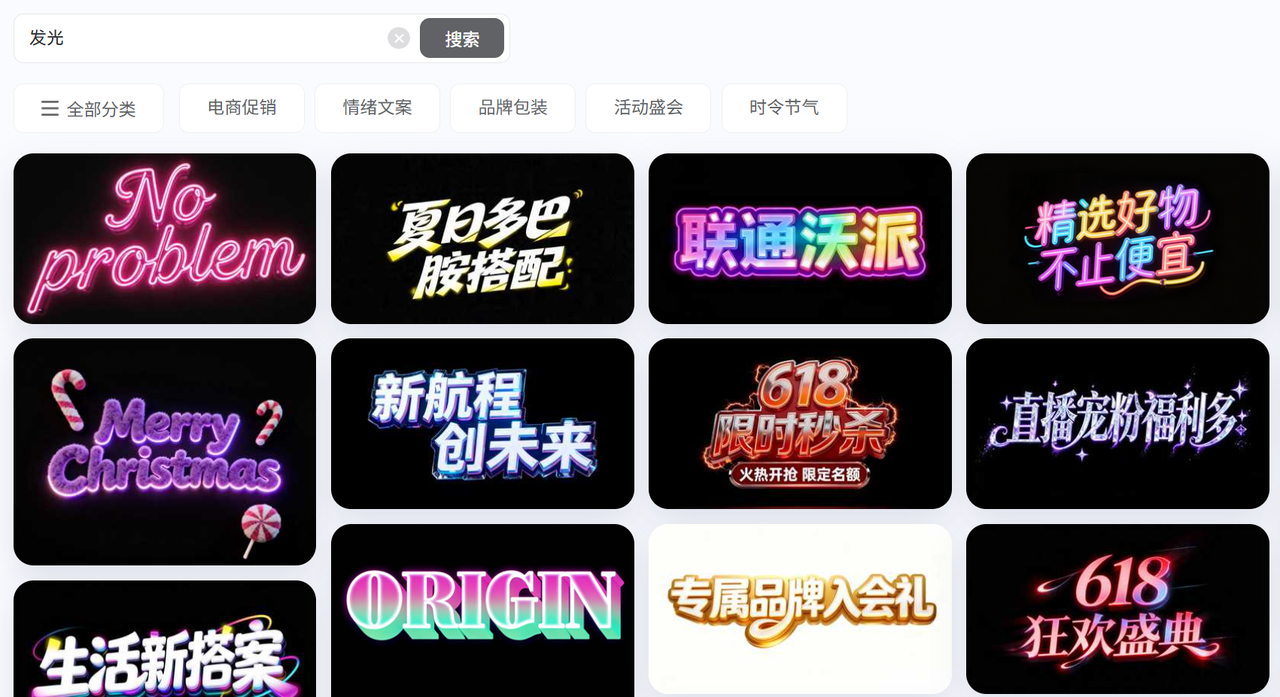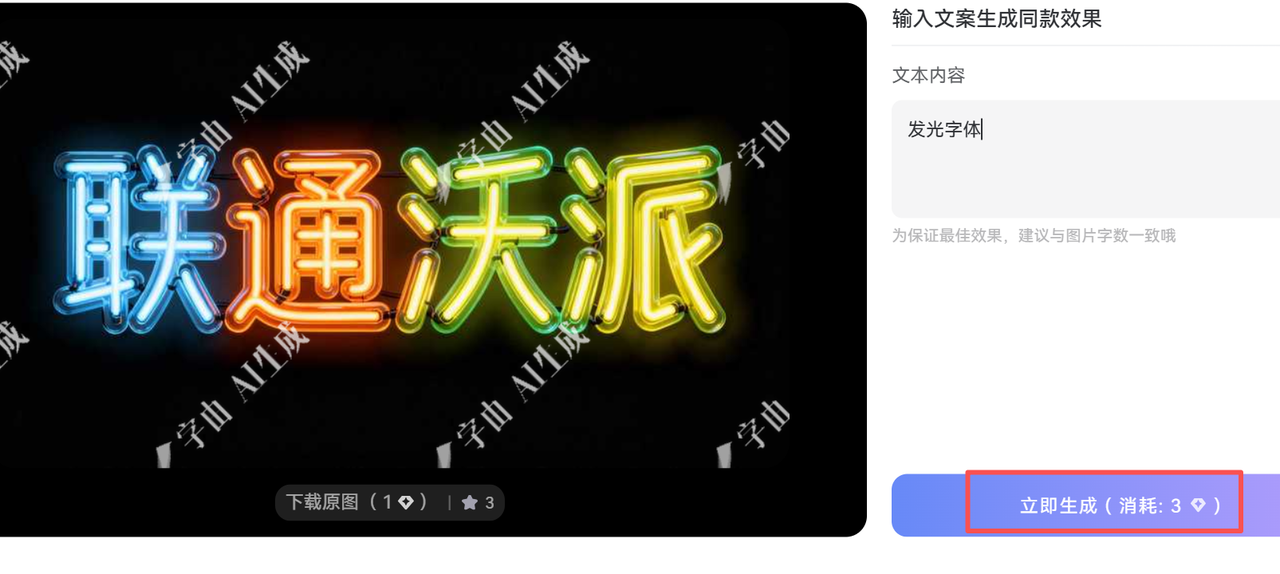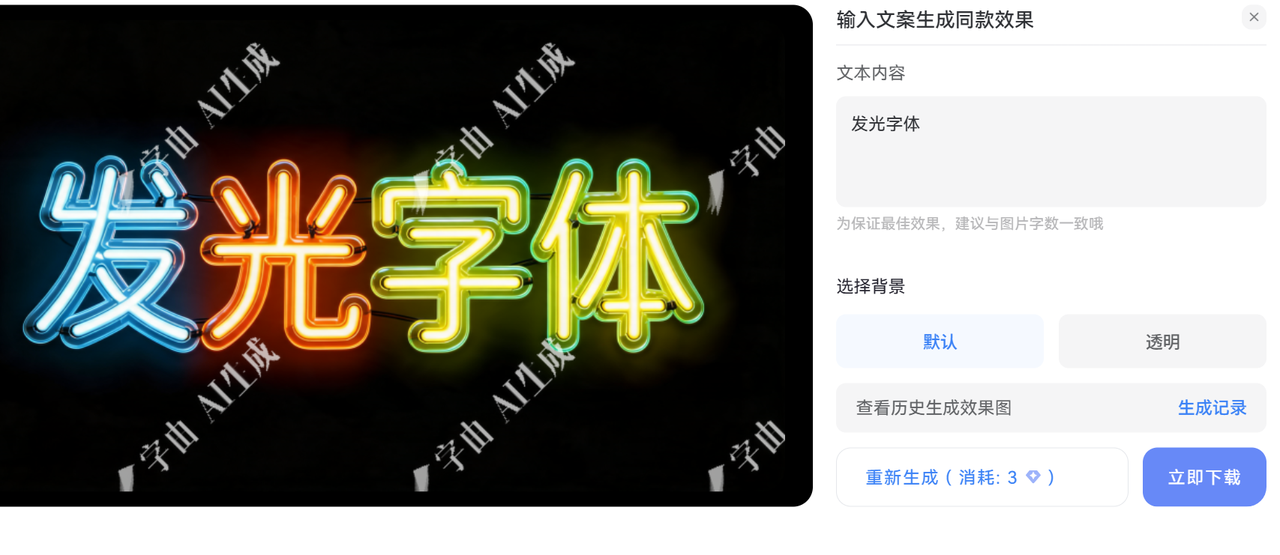
免费商用发光字体下载教程,AI生成发光字体方法
发光字体,因为其独特的光影效果,能够瞬间提升视觉冲击力和美感。然而,许多设计师和创作者在寻找免费且可商用的发光字体时,非常困难,作为一名长期从事设计和内容创作的人,今天,我将分享一个完整的免费商用发光字体下载教程,帮助你快速获取合适的字体资源,掌握简单的发光效果制作方法,掌握这些内容后,你可以轻松应用发光字体于海报、网页、视频甚至品牌标识设计,提升作品的专业度和吸引力。
一、字由AI字体
字由AI字体是一种基于人工智能技术的字体生成与设计平台。平台提供多种字体模板,涵盖现代、复古、手写等多样风格。无需手动绘制,快速生成所需字体,大幅节省设计时间。对于想要制作发光字体效果的朋友来说,字由AI生成字体是个非常好的选择
二、发光字体下载
访问官网
搜索发光字体
页面内置多款字体模板,搜索栏可输入“发光字体”或“光影字体”关键词筛选。
选择合适字体
挑选你喜欢且符合设计主题的发光字体
生成发光字体
输入自己的文字,点击一键生成,等待几十秒后就可以完成字体生成
下载发光字体
点击下载按钮,即可把字体下载到本地,方便应用到你的作品中
通过以上步骤,你可以获得质量较高、且无版权顾虑的发光字体文件。在设计中直接使用这些字体,既节省时间又保证合规。
三、常见发光字体模板推荐
最近我使用字由AI字体比较多,给大家分享几款我认为比较好看的发光字体模板。
心动好礼,为爱放价
比较典型的有关“爱”的节日宣传都可以使用,比如520、情人节、母亲节、父亲节等等
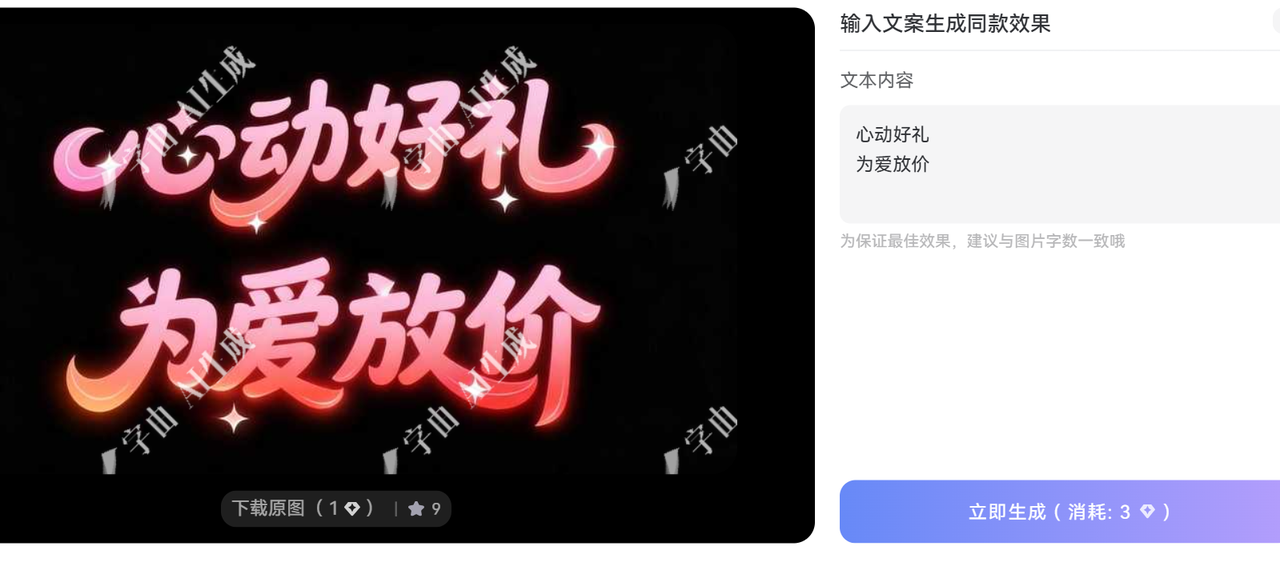
电音派对
适合电音、说唱、嘻哈等潮流场景
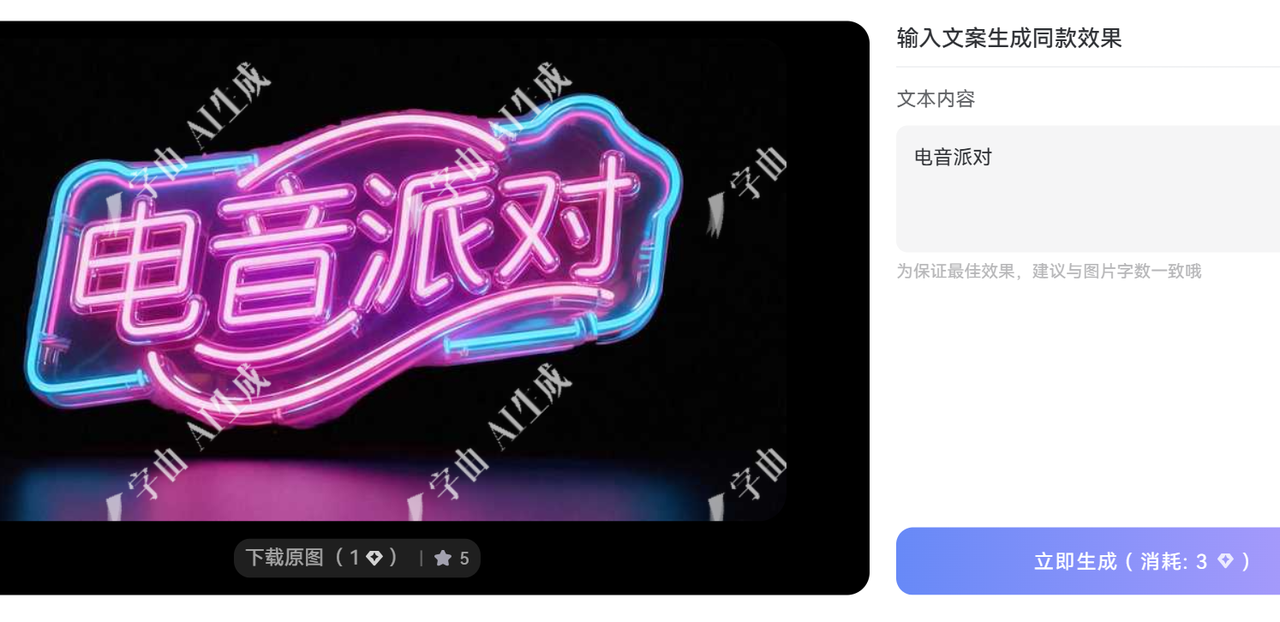
星光游乐园
适合综艺、娱乐等方向
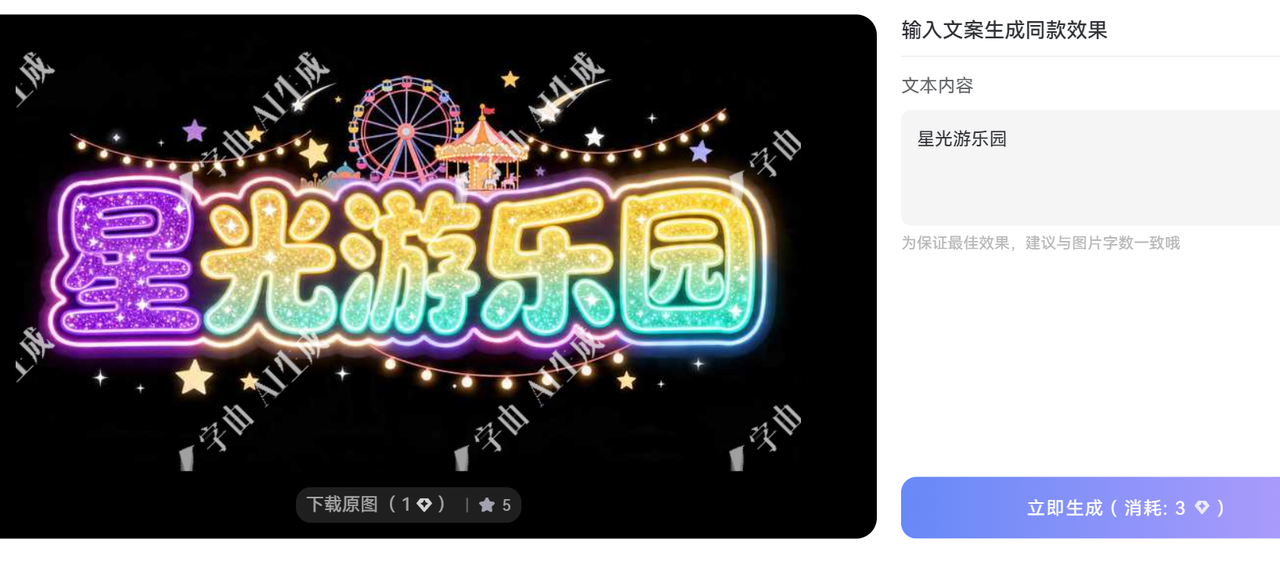
四、AI生成发光字体的常见问题
在使用过程中,我也遇到并总结了一些常见问题,希望能帮到你:
Q2:AI生成的发光字体能修改颜色和大小吗?
A:一般导出的图像文件颜色固定,若想更改需在矢量编辑软件中调整。
Q3:AI生成的发光效果会不会显得不自然?
A:不会,只要你选择匹配的发光字体模板,你就可以生成同款的效果,不会显得不自然
通过本文,我分享了免费商用发光字体下载的实用方法,并介绍了利用AI技术生成发光字体的技巧。结合这些内容,任何设计师和内容创作者都能轻松提升作品的视觉表现力。希望你也能在实践中发现更多灵感,创作出独具风格的作品。